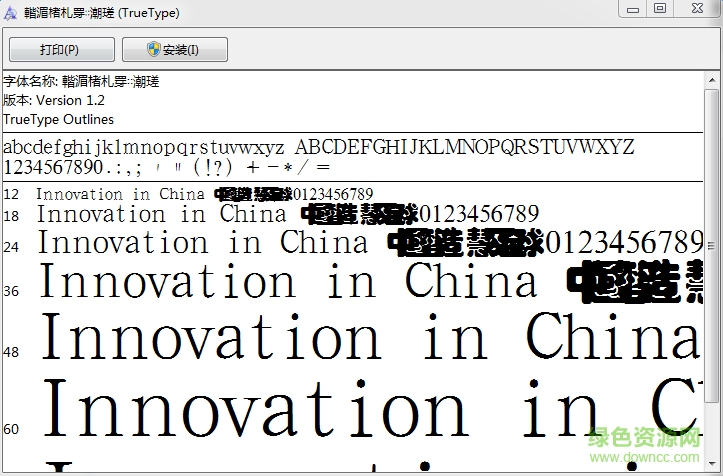
漢鼎繁琥珀字體是一種很有特色的字體,這種字體寫出來的字比較粗厚,但是給人一種很穩(wěn)重的感覺,可用于書法題詞、廣告標(biāo)題等,歡迎有需要的朋友來綠色資源網(wǎng)下載。
字體效果很隨意,讓人看著很舒服,整體字形充滿時(shí)代感,效果良好,可應(yīng)用于文學(xué)設(shè)計(jì)、藝術(shù)創(chuàng)作、平面廣告、印刷包裝等領(lǐng)域,